Der beste kostenlose Schriftarten generator 2026. Mach deinen Instagram, TikTok & WhatsApp Text sofort auffällig!
Mal ehrlich: Wer bleibt bei einer langweiligen Bio wie „hey follow me“ wirklich stehen? In 2026 dreht sich alles um Ästhetik, starke Vibes oder diesen soften, süßen Look. Und der einfachste Weg, das zu bekommen – ohne einen einzigen Cent auszugeben – ist ein guter Schriftarten generator (auch bekannt als Font Generator oder Fancy Text Tool).
Du gibst einfach deinen Namen, ein Zitat, deine Bio oder eine Caption ein – und zack – bekommst du in Sekunden unzählige stylische Versionen. Realistische Handschrift, runde Bubble-Schriften, dicke Graffiti-Styles, elegante Kalligrafie, Retro-Vibes, Glitch-Effekte, Spiegeltext, Small Caps, Herzen, Sterne, saisonale Designs wie Halloween oder Weihnachten – alles dabei. Stil auswählen, kopieren, einfügen – fertig. Funktioniert auf Instagram, TikTok, WhatsApp, YouTube, Roblox, Canva, Discord und fast überall sonst.
Und ja es macht wirklich einen Unterschied. Ändere deine Bio oder deinen Benutzernamen zu etwas Stylischem und plötzlich bekommst du mehr Profilklicks, Likes, Kommentare und Follower. Kleine Änderung, große Wirkung.
Was macht einen guten kostenlosen Schriftarten generator 2026 aus?
Nicht alle sind gleich gut. Manche sind langsam, voll mit nerviger Werbung oder bieten nur fünf langweilige Optionen. Die richtig Guten dagegen überzeugen mit:
Hunderte nützliche Styles
200 bis 400+ Variationen:
- echte Schreibschrift
- fette TikTok-Schriften
- runde Bubble-Lettern
- Graffiti-Styles
- Retro 80er/90er Look
- minimal & clean
- ästhetische Schriften mit Symbolen
- Glitch & Distorted
- Spiegeltext
- Small Caps
- Emoji-Mix
- saisonale Designs
Neue Trends wie Vaporwave oder „Cursed Text“ kommen regelmäßig dazu.
Sofortige Ergebnisse
Einmal tippen – alle Varianten erscheinen direkt. Kein 50x auf „Generieren“ klicken.
Funktioniert überall
Dank Unicode werden die Schriften korrekt angezeigt auf:
Instagram, TikTok, WhatsApp, YouTube, Roblox, Discord, Pinterest, Canva, Twitter/X usw.
Nicht alle sind gleich gut. Manche sind langsam, voll mit nerviger Werbung oder bieten nur fünf langweilige Optionen. Die richtig Guten dagegen überzeugen mit:
Hunderte nützliche Styles
200 bis 400+ Variationen:
- echte Schreibschrift
- fette TikTok-Schriften
- runde Bubble-Lettern
- Graffiti-Styles
- Retro 80er/90er Look
- minimal & clean
- ästhetische Schriften mit Symbolen
- Glitch & Distorted
- Spiegeltext
- Small Caps
- Emoji-Mix
- saisonale Designs
Neue Trends wie Vaporwave oder „Cursed Text“ kommen regelmäßig dazu.
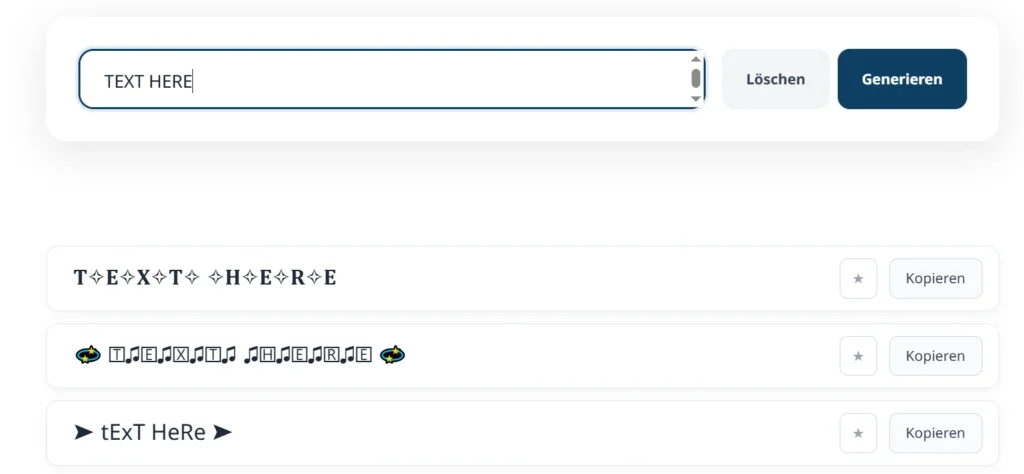
Sofortige Ergebnisse
Einmal tippen – alle Varianten erscheinen direkt. Kein 50x auf „Generieren“ klicken.
Die besten Seiten halten es sauber und schnell.
Funktioniert überall
Dank Unicode werden die Schriften korrekt angezeigt auf:
Instagram, TikTok, WhatsApp, YouTube, Roblox, Discord, Pinterest, Canva, Twitter/X usw.
Was ist ein Schriftgenerator und warum brauchst du ihn?
Ein Schriftgenerator ist ein Online-Tool, das normalen Text mithilfe spezieller Unicode-Zeichen in Hunderte stylische Varianten umwandelt. Du musst nichts herunterladen und brauchst keine Design-Kenntnisse.
Einfach Namen oder Text eingeben → Stil auswählen → kopieren → einfügen.
Warum lohnt sich das?
- Mehr Profilklicks
- Mehr Likes & Kommentare
- Dein Profil wirkt kreativer & professioneller
- Perfekt für ästhetische Social-Media-Vibes
In 2026 setzen fast alle auf stylischen Text.
So benutzt du einen Schriftgenerator:
- Öffne einen guten Schriftgenerator.
- Tippe deinen Text ein.
- Wähle deinen Lieblingsstil.
- Klicke auf „Kopieren“.
- Füge ihn in Bio, Username oder Caption ein.
Fertig in unter 10 Sekunden.
Beliebte Stil-Kategorien
Handschrift & Schreibschrift
Sieht aus wie echte Handschrift – perfekt für Bios oder WhatsApp.
Kalligrafie
Elegant & ästhetisch – ideal für Instagram oder YouTube.
Fett & Bold
Perfekt für TikTok oder Roblox, wenn du auffallen willst.
Minimal & Clean
Modern & professionell – gut für Business-Profile.
Bubble & Verspielt
Rund & lustig – besonders beliebt bei jüngeren TikTok-Usern.
Welche Schrift ist 2026 für Instagram-Bios beliebt?
Softe Kalligrafie oder minimalistischer Stil mit kleinem Herz-Emoji.
Funktioniert das in jeder App?
Fast überall – sehr alte Apps zeigen manchmal Kästchen an.
Hör auf mit langweiligem Standard-Text. Öffne einen Schriftarten generator, tippe etwas ein, wähle deinen Style und mach dein Profil in Sekunden 10-mal interessanter.